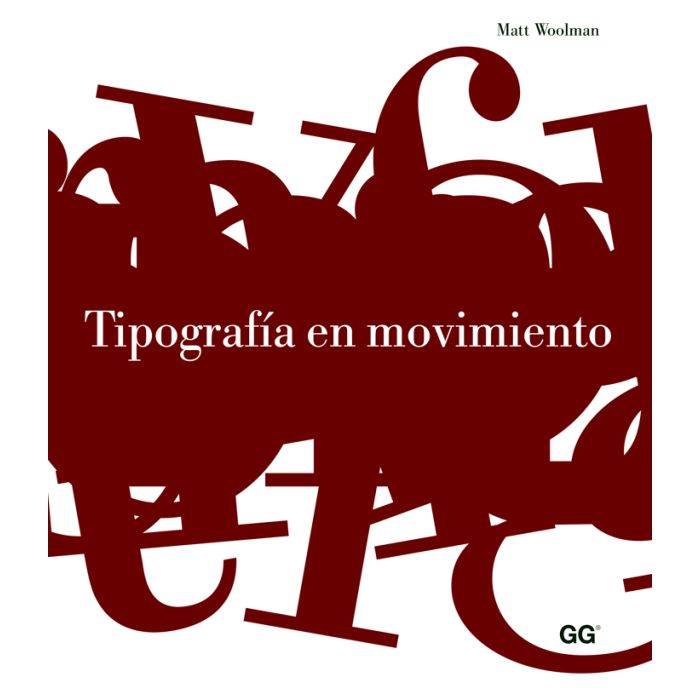
Tipografía en movimiento
Un libro de Matt Woolman
Tipografía en movimiento reúne trabajos de despachos internacionales innovadores: desde estudios unipersonales de carácter muy experimental a grupos de investigación de ámbito internacional que tienen una enorme capacidad para procesar datos. En este libro se analizan con detalle más de ochenta trabajos, ordenados en cinco capítulos que tratan algunos de los continuos retos a los que se enfrentan los diseñadores de hoy en día. 'Identificar' analiza el papel de la tipografía cinética en la creación de imágenes corporativas en diferentes medios, como las marcas de cadenas de televisión, los títulos de programas y las cortinillas de transición. La transmisión de información sobre un producto, un servicio o un acontecimiento mediante un mensaje tipográfico se presenta en el capítulo 'Informar', que incluye anuncios de interés público y publicitarios.
La combinación de palabras, imágenes y sonidos para crear historias y establecer un contexto, es decir, 'Contar historias', analiza los temas relacionados con la narración, en los que el diseñador establece el marco para la historia que quiere contar el cliente. La sección 'Viajar' ubica al usuario en el asiento del conductor, tanto si se trata de navegar por una página web o un programa de software como si el movimiento es físico, e implica desplazarse de un lugar a otro mediante las tecnologías móviles y sus interfaces. Por último, la seccion 'Especular' muestra un amplio espectro de proyectos experimentales, que se sitúan en la vanguardia de la tipografía y el diseño tipográfico, destinados a explorar nuevas ideas, funciones y métodos de comunicación.
Tipografía en movimiento presenta los mejores trabajos de un ámbito que ha evolucionado muy rápidamente (y se encuentra en constante estado de expansión), y donde el diseño contemporáneo ha podido mostrar y desarrollar su verdadero espíritu de innovación e imaginación.
Índice de contenidos:
Introducción
01 Identificar
Aires callejeros: EyeballNYC
En la cancha: EyeballNYC
Inspiración musical: Michael Feldman
Revivir el pasado: Michael Feldman
El espacio intermedio: P2
Cálido y peludo: Lobo
Belleza sublimada: Lobo
Funk y groove: GMUNK
Rápido y furioso: GMUNK
Elegancia urbana: FUEL
Infestación tipográfica: Tronic Studio
Dar fuego a la anticipación: Montgomery and Co. Creative
Definir el género: Montgomery and Co. Creative
Al final de la cadena de alimentos: Montgomery and Co. Creative
Simplicidad escandinava: Stockholm Design Lab
A caballo de la música: Digital Kitchen
Tipografía emotiva: Virginia Commonwealth University
En juego: Virginia Commonwealth University
Sierras caladoras y motores V-Rod: M+Motive
Atrapar el instante: M+Motive
Una tipografía de miedo: mOcean
Sazonar las noticias: Koo-Ki Motion Graphics
Claridad formal: Trollbäck and Co.
La reinvención del libro: Trollbäck and Co.
Tipografía conceptual: Universidad Libanesa Americana
02 Informar
Tipografía omnisciente: Arthur Kuhn
Forma y contraforma: Virginia Commonwealth University
Cultura digital: Foreign Office
Protegiendo de la creatividad: Digital Kitchen
Ensayo audiovisual: Universidad Libanesa Americana
Tomar el pelo a los conversos: FUEL
Serifas que sudan: FUEL
Une los puntos: FUEL
Lecciones de historia: Carnegie Mellon University
03 Contar historias
Caracteres íntimos: Mirko Ilic
Tipografías atléticas: Mirko Ilic
De lo personal a lo universal: California College of Arts
Narrativas iluminadas: Montgomery and Co. Creative
Examinar los detalles: Montgomery and Co. Creative
Bar Coyote Ugly: Montgomery and Co. Creative
Atrapar a los clásicos: Trollbäck and Co.
Tipografía ciega: Trollbäck and Co.
Poesía visual: Trollbäck and Co.
Movimiento lírico: InterStitch Films
Elegancia intemporal: InterStitch Films
Disección formal: InterStitch Films
Síntesis contraformal: InterStitch Films
Visualizar conversaciones: Garry Waller